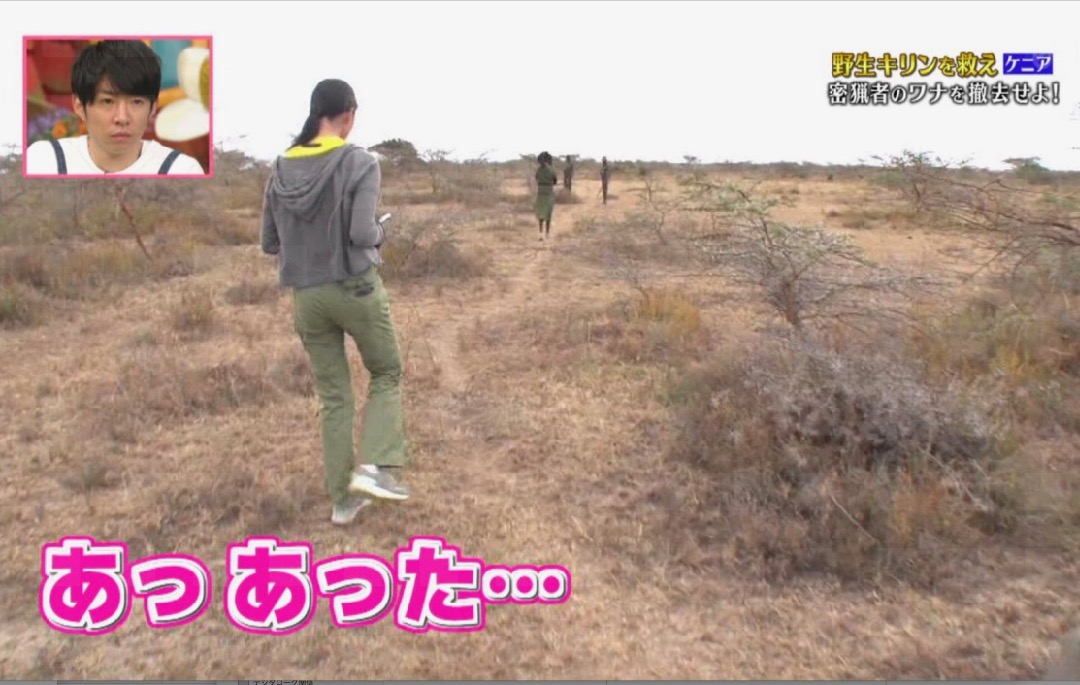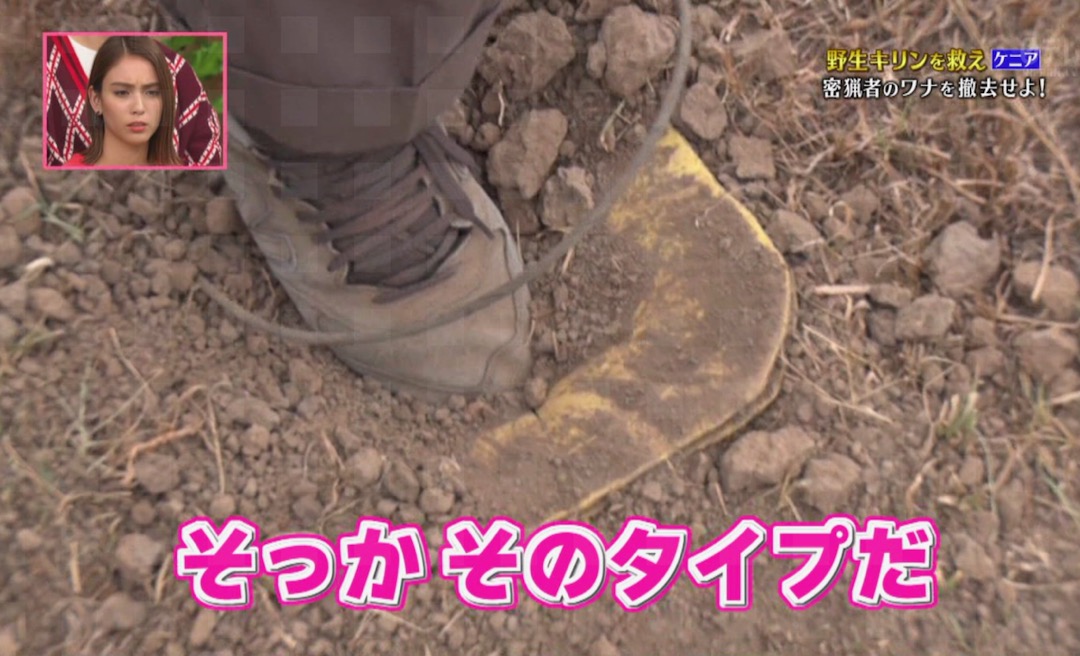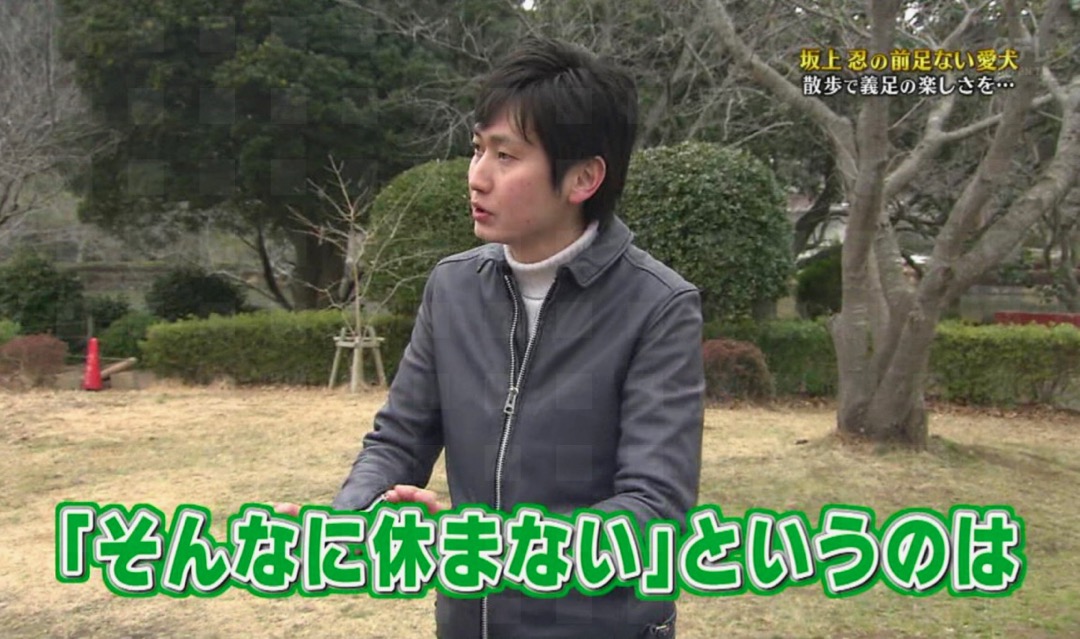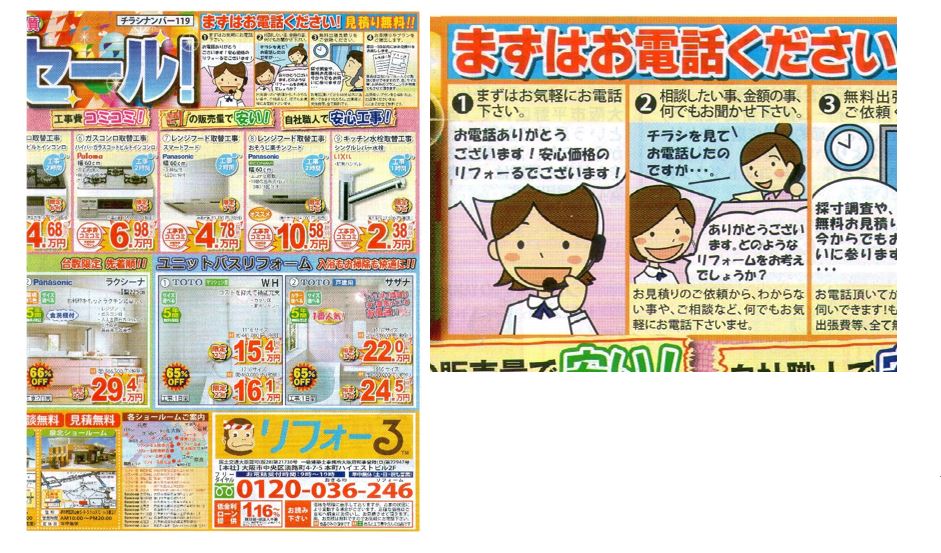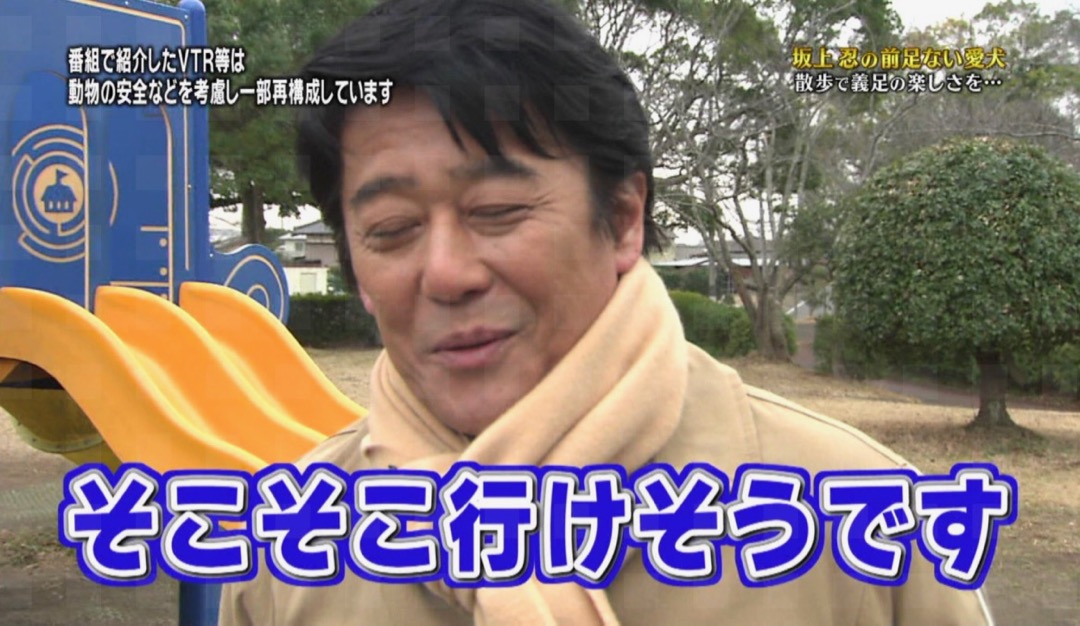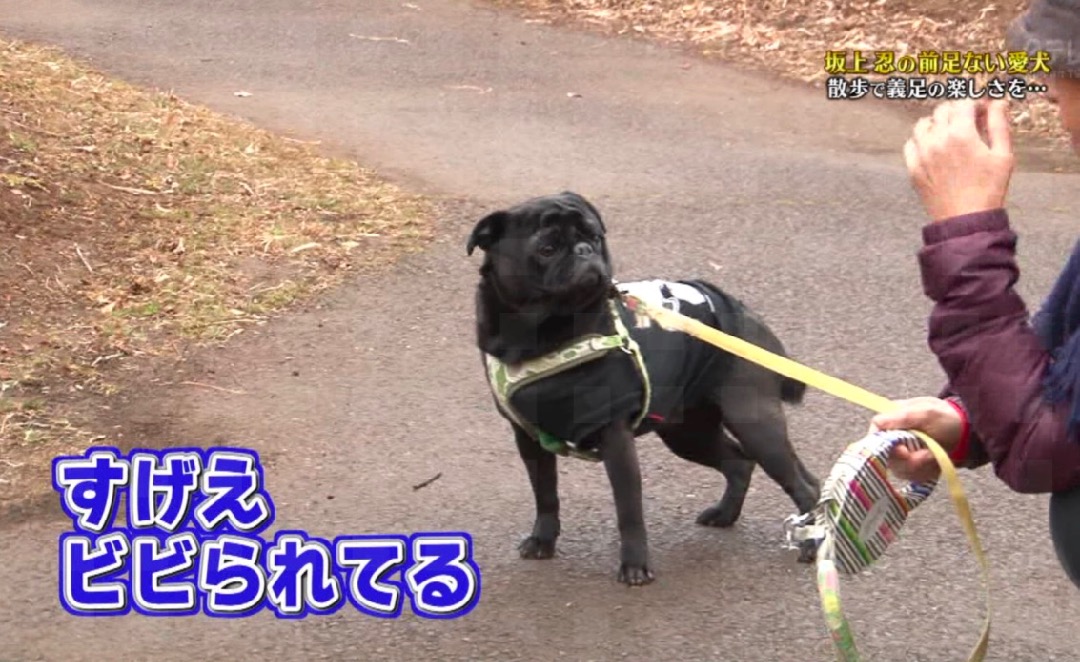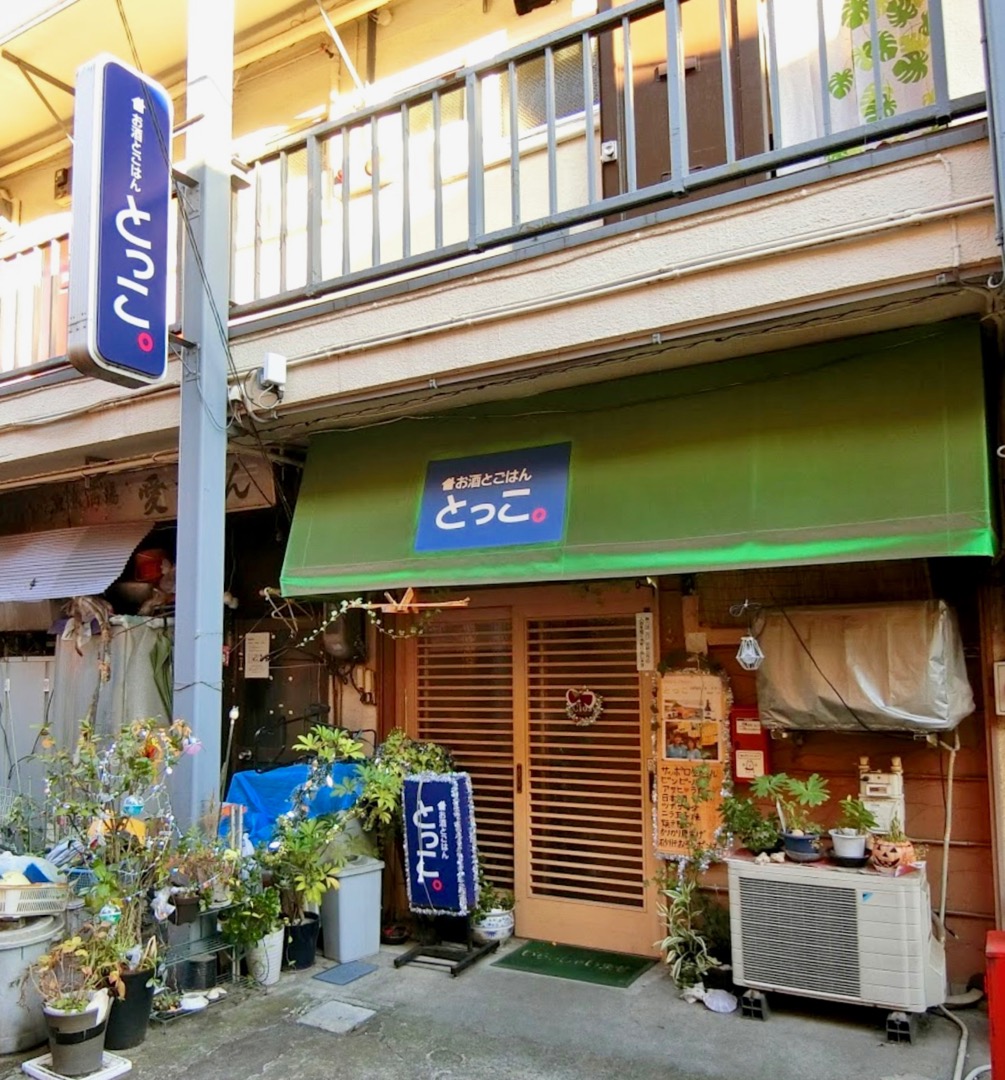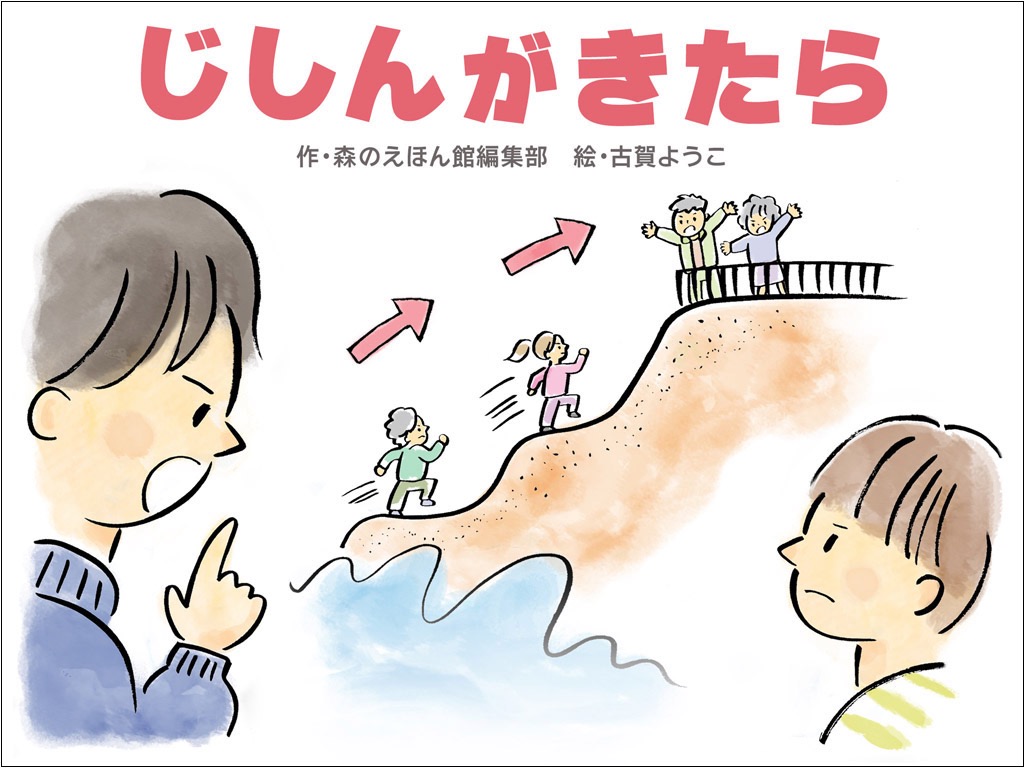
スライドえほん  さとうゆたか  2019年1月5日(土) 10:11
書名:アンパンマンとかくれんぼ!
著者:やなせたかし
発行:フレーベル館
写植用?のわんぱくフォント  takumi  2018年12月31日(月) 1:16  HP
佐藤さん、こんばんは。
デパートの食品売り場で見かけた「わんぱく」です。
現行のものと異なるデザインですが、写植用のわんぱくフォントですかね…?(↓など拝見しました)
なんでしょうね? 原型はわんぱくだと思いますが、トレスしたのかな?
「が」は形が崩れているし、オリジナルの作者としては目をそむけたくなる感じです…。
子ども新聞  大阪のうめ吉  2018年12月30日(日) 4:23  Mail
読売新聞社が発行している「読売KODOMO新聞」(週刊)12月7日号の連載もののタイトルです。
タブロイド判の紙面。画像は上半分のみです。
左上「わかったぞ」のタイトルロゴ。
賀状イラスト  大阪の  2018年12月28日(金) 4:18  Mail
会員になっており、見出しの背景・地紋として利用しているイラストACの投稿サイトに投稿されものです。
この2種の他にもイラストのみが異なるものが複数あります。「しゅんぴ」さんという方の作品です。
アンパンマンシリーズ  大阪のうめ吉  2018年11月22日(木) 2:23  Mail
大阪市平野区SS書籍売り場で見つけました。
「パトロールにいってきます」
発行・フレーベル館
シリーズの仕掛け絵本
作画・やなせたかしさん
ページを見開きにすると立体になるしかけの本です
この画像、私の方でも見つけて用意してました…。
シリーズ  大阪のうめ吉  2018年11月22日(木) 8:49  Mail [修正]
そうでしたか。でしたらシリーズで4種類あることも気づかれたと思います。一応全部の写真を撮ってきましたが。
中身(本文)の台紙になる紙は分厚いですが、本そのものはコンパクトなものです。
「かくれんぼ」「どんなかお」「いろがへんしん」「ピンポーン」は確保してあります。
そのうちに、このスレッドに加えていこうと思います。
どんなかお?
いろがへんしん!
ピンポーン!
シールブック  大阪のうめ吉  2018年11月21日(水) 14:44  Mail
今日、大阪市平野区のSS書籍売り場で見つけました。
ロゴタイトルに使用されています。
講談社「たの幼テレビデラックスHUGっとプリキュアオールスターズ ま るごとシールブック」
で検索してみてください。講談社のサイトが鮮明な写真です。
本と言うよりノートくらいの厚さ、B6変形の小さなサイズのシールブックです。
これですかね?
これです。  大阪のうめ吉  2018年11月21日(水) 17:13  Mail [修正]
この本です。本といっても小さいですけど「わんぱく」は大きく使われています(感激!!)。
ぬりえ  大阪のうめ吉  2018年11月27日(火) 18:18  Mail
今日、平野区のSS売り場で見つけたものです。いつもと違うSSです。
「たっぷりあそべるかわいいぬりえ」
発売・東京書店
発売・11月20日
ぬりえ本というより文具って感じです。形状は本のようですが、観音開※ きで、中に24色の色鉛筆とぬりえが入っています。
※仏壇のトビラのように、中央から左右に開くようにしたもの。折り方と しては「観音折り」と言います。
ぬりえ  大阪のうめ吉  2018年11月27日(火) 18:26  Mail [修正]
これは通販サイトのものです。
実際の商品ではなく、印刷時の原版写真のようです。実際の商品には上の実写のようにリボンもついており、中央が開くようになっています。
ふるさと小包カタログ  大阪のうめ吉  2018年11月21日(水) 15:41  Mail
郵便局のふるさと小包のカタログです。
今日、郵便局に寄った時に見つけたのですが、東京本社制作ですので、近くの郵便局にもあると思いますが…
主タイトルはFWさんので、主タイトルでないのがちょっと残念ですが(笑=FWさんごめん)。
土産品  さとうゆたか  2018年11月14日(水) 21:11
和歌山アドベンチャーワールドの売店で。
パッケージの側面。
しかけえほん  さとうゆたか  2018年11月7日(水) 9:34
書名:F1レースであそぼうよ
著者:サム・タプリン、ポール・ニコルス
発行:大日本絵画